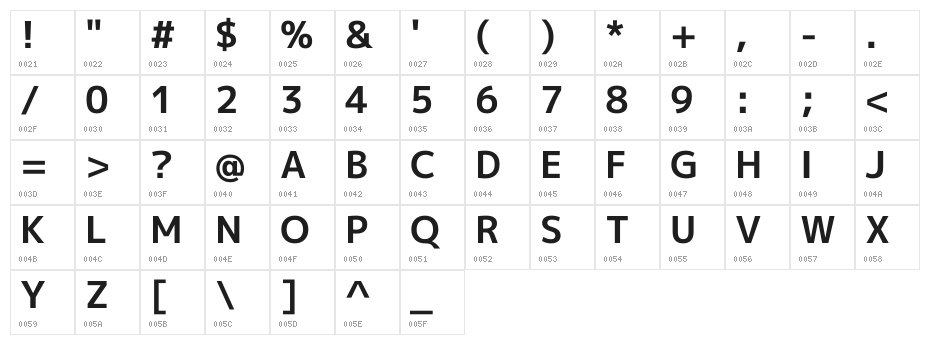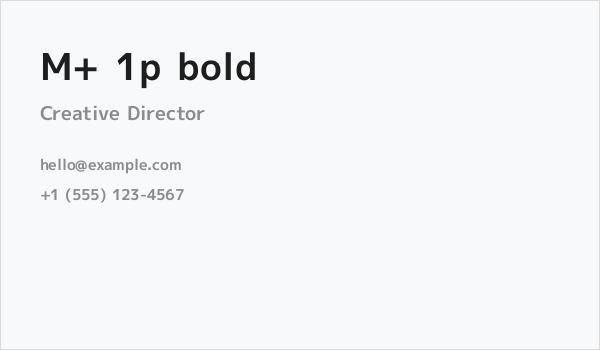
M+ 1p bold Font
Questo font include 5446 caratteri. Clicca su un carattere per vedere i dettagli.
| Caso d'uso | Headlines, Logos, Branding |
| Progetti proposti | Ideal for branding, advertising, headlines, and digital media where clarity and impact are essential. |